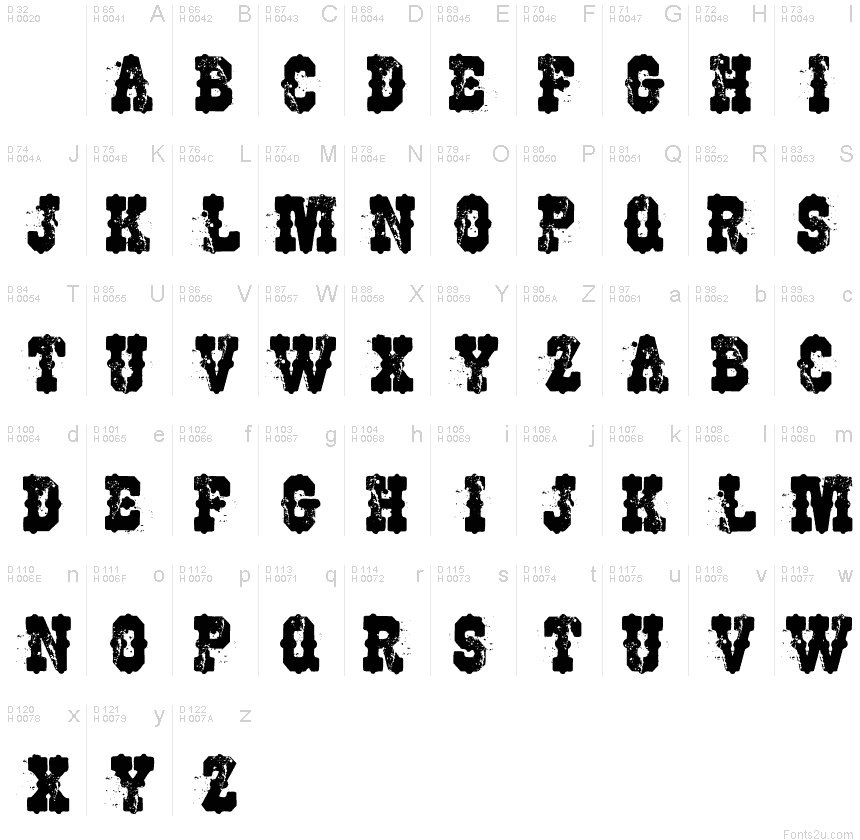
Working Class Hero ist eine kostenlose, verwitterte Western-Display-Schrift vom Designer hydro74 – hat dieses Biest rausgehauen! Massive Slab-Serif-Versalien tragen tiefe Abplatzungen, abgeriebene Stellen und ausgefranste Kanten über ihre breiten Formen. Die Beschädigung ist expressiv und unregelmäßig.
Western- und Outlaw-Themen machen sie zu einer überzeugenden Wahl für Musikplakate, Bar-Branding und robustes Merchandise. Ihre spritzige Patina kann Staub, Rauch, abgeblätterte Farbe oder abgenutzte Fotografie widerspiegeln, sodass Event-Grafiken und Albumcover das Lettering direkt in ihre Bildsprache integrieren.